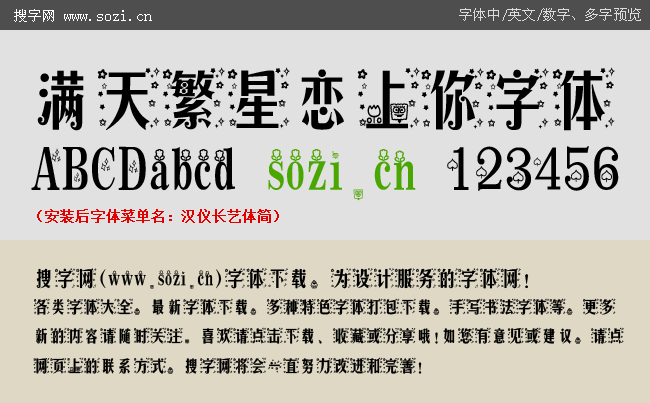
滿天繁星戀上你字體
搜字網給大家提供一款滿天繁星戀上你字體手機中文字體下載。這款手機字體是在漢儀長藝體筆畫間插入了卡通星星圖案。長藝體既有黑體的粗壯醒目,又有宋體的秀美柔和,加上藝術性的圓球形點、起筆如蝌蚪形的頓點、螺螄轉似的小鉤,配以修長的字形,如少女般婷婷玉立,裊娜動人,美觀而不落俗套。加入了卡通圖案后又增添了藝術性,特別適合喜歡手機字體個性一些的朋友在手機上安裝使用。